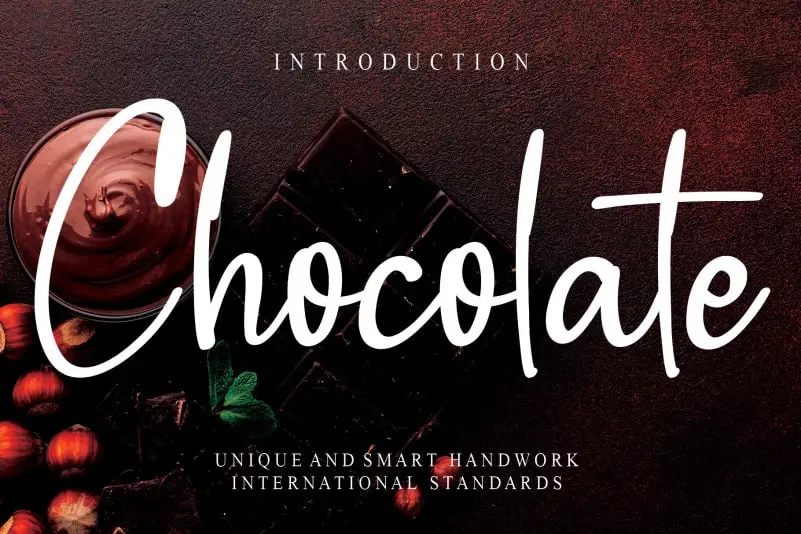
Chocolate Script Font é uma fonte handwritten que vai fazer sua arte digital ganhar vida ao deslizar seus olhos por ela. Esta fonte foi criada pelo designer creativeletter e oferece um toque especial, permitindo que você crie designs únicos e memoráveis sem grandes esforços. Com seu design fluido e contínuo, Chocolate Script Font é perfeita para adicionar uma pitada de personalidade a qualquer projeto. Perfeito para uso em mensagens digitais, letras para o blog ou até mesmo para criações gráficas mais elaboradas, esta fonte oferece um toque único que pode tornar seus projetos ainda mais únicos e encantadores. Para quem busca algo diferente e especial para dar vida aos seus designs digitais, Chocolate Script Font é a escolha perfeita. Sem dúvidas, ela se destaca como uma das melhores fontes handwritten no mercado atual.